フォントを作る人に聞いてみた その3:好きなひらがなグリフ2
タイププロジェクトのスタッフ達に「好きなひらがなグリフ」は何かを聞いてみました。
前回の記事ではひらがなのデザインに言及したも回答を紹介しましたが、今回はその次に多かった「名前に使われている文字」というものを紹介します。
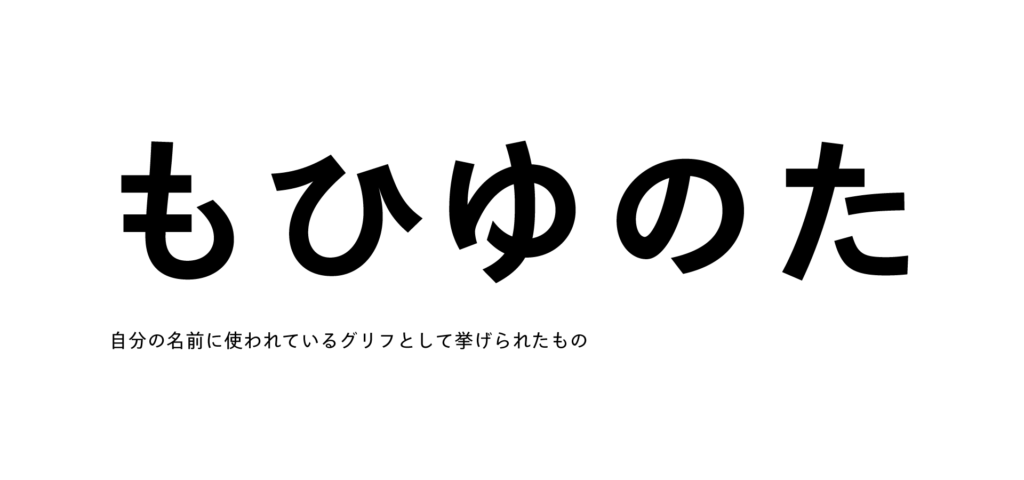
- も:
自分の名前に入ってることもあり常に向き合ってきた文字だと思います。シルエットはスマートに、横画は繋げて書くのが好きです。
- ひ:
「ひ」は名前で一番よく書くのにうまく書けたと思ったことが一度もないので好きというか見るときに気になる文字です。
- ゆ:
丸みのある形が好きというのに加えて、自分の名前に使われているので、書体を見る時にはついつい「ゆ」の形が好みかどうかを気にしてしまいます。 自分で書くときは一筆書きにするのが好きです。
- の、た:
自分の名前にあるので好きです。
やはり自分の名前に使われているものは目にする機会・書く機会ともに多いので気になってしまう人が多いようで、自分で書く時のこだわりがある点も面白いです。